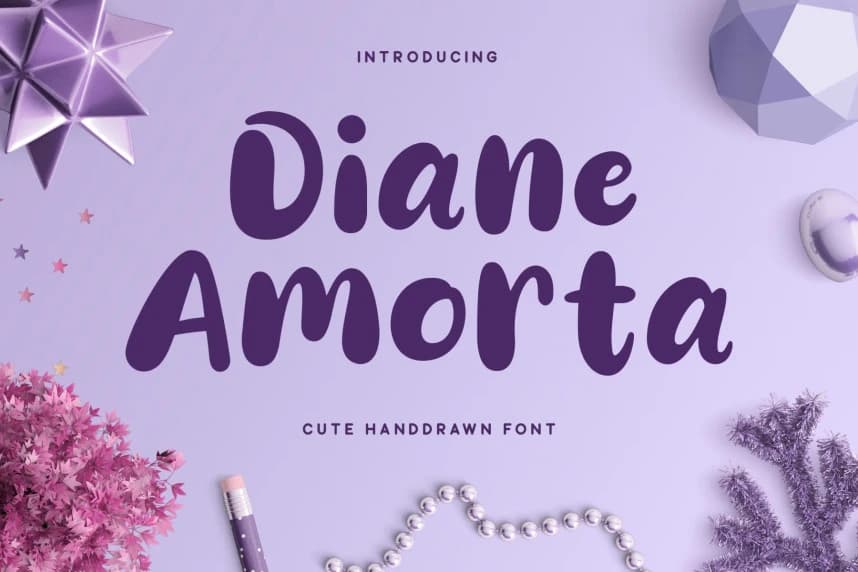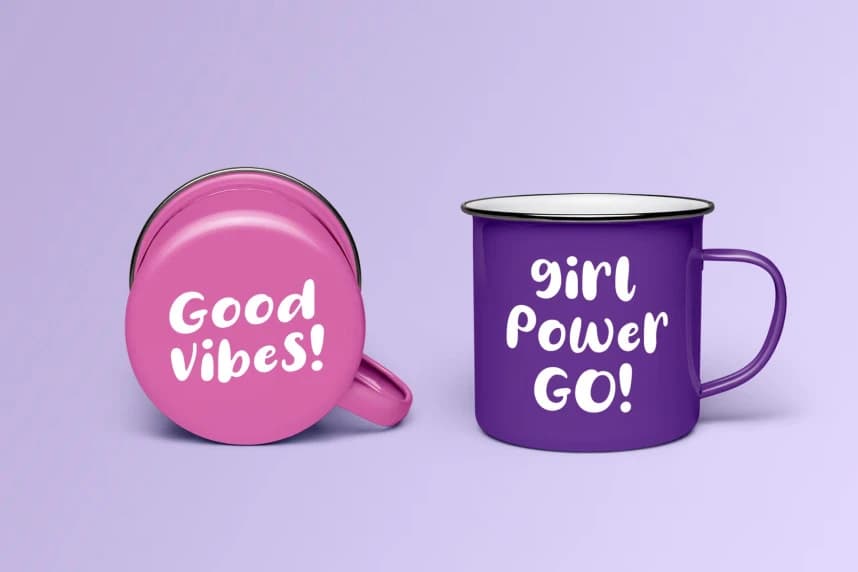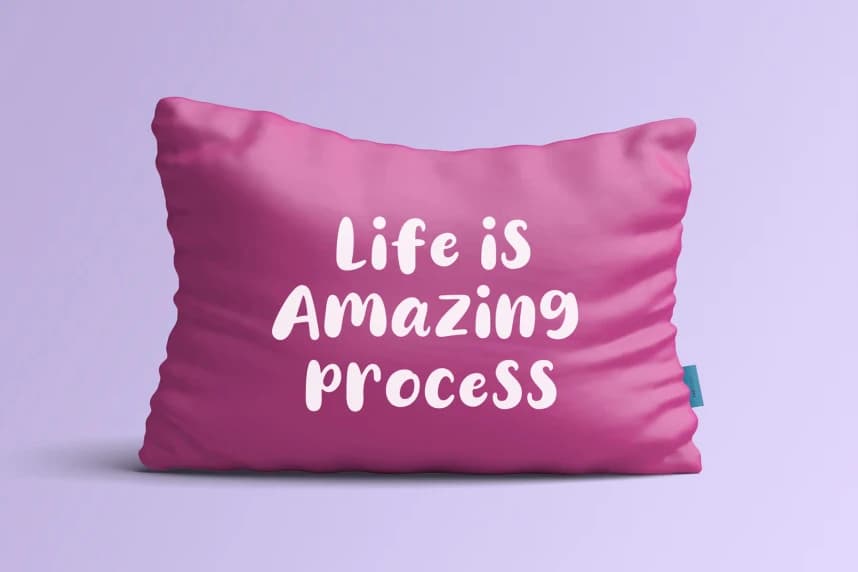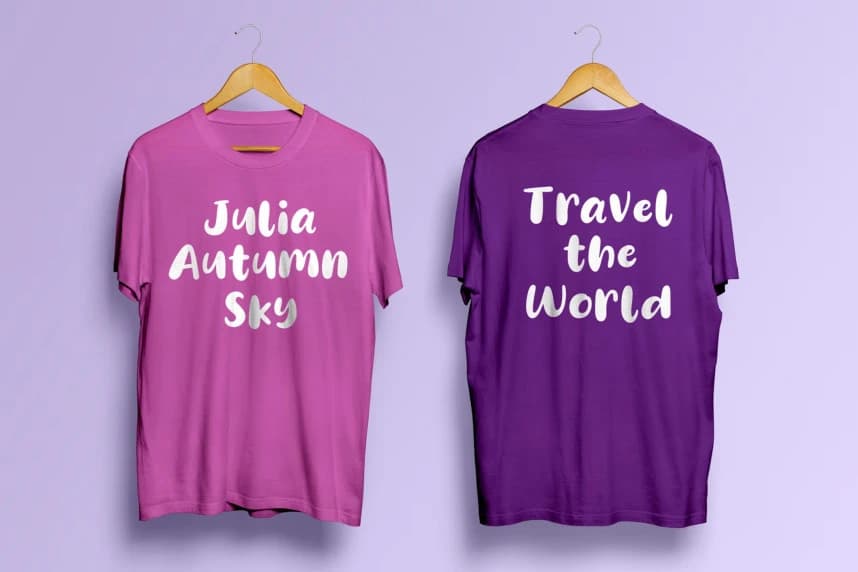
Diane Amorta Font
Diane Amorta Font, çok özenle tasarlanmış sevimli bir el çizimi sans-serif yazı tipidir. Diane Amorta, branding için logo tasarımında, tipografi tasarımında, ürün ambalajında, davetiyelerde, alıntılar için, tişört tasarımında, etiket posterlerinde, özel etkinliklerde ve el yazısı hissi gereken her d
Diane Amorta Font, çok özenle tasarlanmış sevimli bir el çizimi sans serif fontudur. Diane Amorta, markalaşma için logo tasarımı, tipografi tasarımı, ürün ambalajı, davetiyeler, alıntılar, tişört tasarımı, etiket afişi, özel etkinlikler ve el yazısı tadına ihtiyaç duyan her şey için mükemmel bir tercihtir.